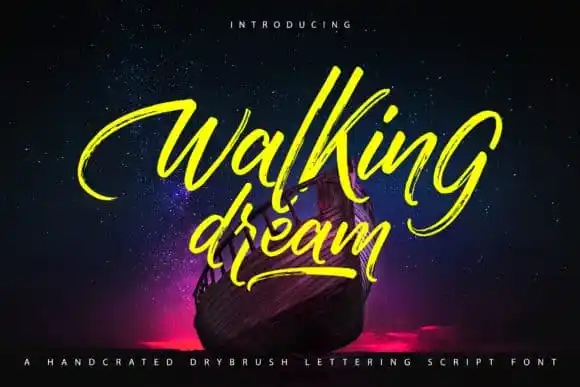
Walking Dream Brush Font – Download Grátis
Descubra uma nova opção para seus projetos digitais com a Walking Dream Brush Font. Esta é uma tipografia script bold e deslumbrante, feita a partir de um estilo único conhecido como dry brush, que oferece um toque vibrante e brilhante às criações. Os designers da 99designs criaram este recurso visual com um designer chamado Vunira, que certamente dará uma verdadeira atenção especial a qualquer ideia de design que você possa ter. A Walking Dream Brush Font será perfeita para aplicações em fitas de propaganda, embalagens, avisos, cabeçalhos de marca e até mesmo signboard urbanos. Ela tem um toque urbano que irá agregar uma nova dimensão aos seus projetos digitais, tornando-os ainda mais inovadores e atraentes. Seja para um projeto digital ou impresso, essa fonte certamente ajudará você a dar ao seu trabalho um toque único e autêntico.